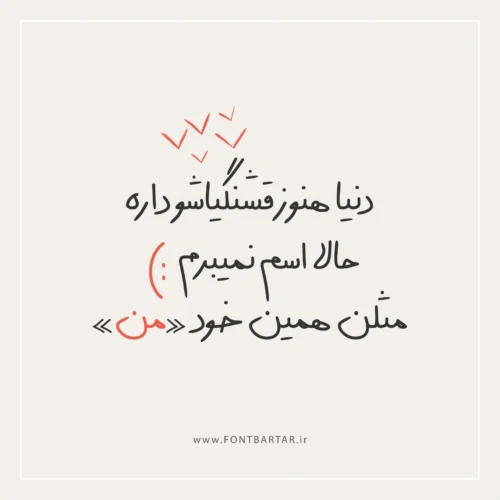
فونت پاییز
دانلود فونت پاییز – فونت فارسی زیبا و احساسی برای طراحی
معرفی فونت پاییز
فونت فارسی پاییز یک فونت زیبا و خلاقانه است که با الهام از حال‌وهوای عاشقانه و رنگارنگ فصل پاییز طراحی شده است. دانلود فونت فارسی به دلیل طراحی خاص و منحصر‌به‌فرد خود، گزینه‌ای ایده‌آل برای طراحانی است که به دنبال فونت احساسی، خلاقانه و متفاوت هستند.
با استفاده از فونت جدید پاییز، می‌توانید پروژه‌های خود را با حس نوستالژی، آرامش و زیبایی همراه کنید و نوشته‌هایتان جلوه‌ای تازه و چشم‌نواز پیدا کنند.
ویژگی‌ های دانلود بهترین فونت فارسی – فونت پاییز
• طراحی الهام‌گرفته از رنگ‌ها و حس پاییز
• مناسب برای پوستر، کارت تبریک، جلد کتاب، تایپوگرافی و استوری اینستاگرام
• ایجاد حس گرما، صمیمیت و آرامش در متن‌ها
فونت جذاب پاییز
چرا فونت پاییز انتخاب مناسبی است؟
دانلود فونت فارسی جدید فونت پاییز فقط یک فونت نیست، بلکه یک حس و تجربه است. وقتی از این فونت در طراحی استفاده می‌کنید، نوشته‌هایتان جان تازه‌ای می‌گیرند و مخاطب با دیدن متن، ارتباطی عاطفی و انسانی برقرار می‌کند. این فونت برای برندها و طراحانی که به دنبال متمایز شدن هستند، یک انتخاب هوشمندانه است.
کاربردهای فونت پاییز
• طراحی پوسترهای هنری و تبلیغاتی با تم پاییزی
• ساخت تایپوگرافی‌های احساسی و نوستالژی
• طراحی جلد کتاب و دفترچه‌هاپ
• استفاده در پست و استوری‌های اینستاگرام
• طراحی کارت دعوت، کارت تبریک و محصولات چاپی
• ایده‌آل برای پروژه‌های خلاقانه و شخصی